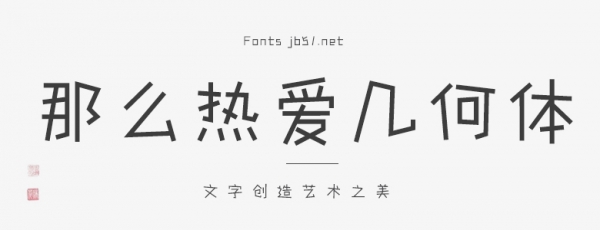
那么熱愛幾何體的靈感源于數(shù)學(xué)中的“幾何線條”,簡(jiǎn)約、靈活、多變。幾何體沒有起筆落筆的修飾,僅用幾何線條本身的松緊對(duì)比,使字形空間變的動(dòng)感,產(chǎn)生了平面與空間的聯(lián)動(dòng)轉(zhuǎn)換,給人無限遐想。幾何體共有 Light、Regular、Blod 三個(gè)字重。歡迎喜歡此字體的朋友前來下載使用。
字體名稱:那么熱愛幾何體
字體風(fēng)格:活潑、可愛、 硬朗、卡通、簡(jiǎn)約、有趣
字庫(kù)規(guī)格:3個(gè)字重,符合GB2312-80標(biāo)準(zhǔn),共收錄6763個(gè)中文簡(jiǎn)體漢字和359個(gè)英文數(shù)字標(biāo)點(diǎn)符號(hào)